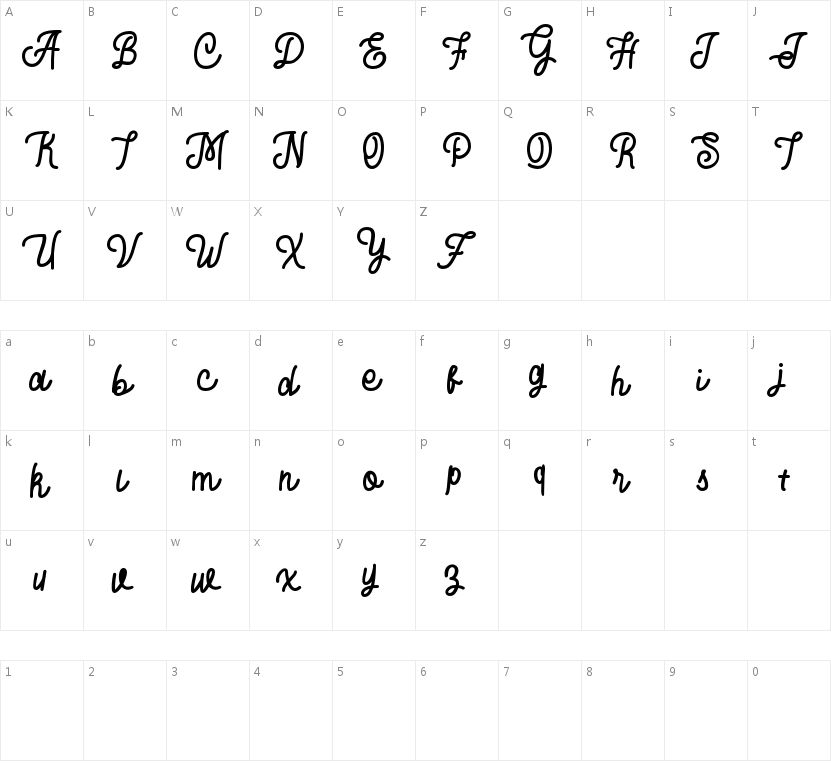
​Bratayuda Free
Bratayuda Free是一款免费字体,它的设计灵感来自印度尼西亚爪哇文化中的传统装饰艺术。这款字体中融合了传统和现代元素,使得它在各种视觉设计方面都能够展现出极高的美感和独特的风格。 Bratayuda Free字体包含了大写字母、小写字母、数字、标点符号等基本字符,并且支持多种语言的书写。除此之外,它还包含了一些特殊符号和装饰性图案,可以用于制作各种印刷品、海报、宣传册等设计作品。 这款字体的特点是线条优美流畅,每个字母都有着独特的装饰性特点,充满了浓郁的艺术气息。Bratayuda Free适用于各种设计场景,如品牌标识、包装设计、广告海报等,可以为设计师提供更多创意和灵感。
​Bratayuda Free是一款非常不错的手写艺术字体,具有很好的视觉感,适合于文化类的宣传设计、商业类品牌的广告和产品包装设计以及个性化文字排版等较多场景。
​Bratayuda Free字符映射图